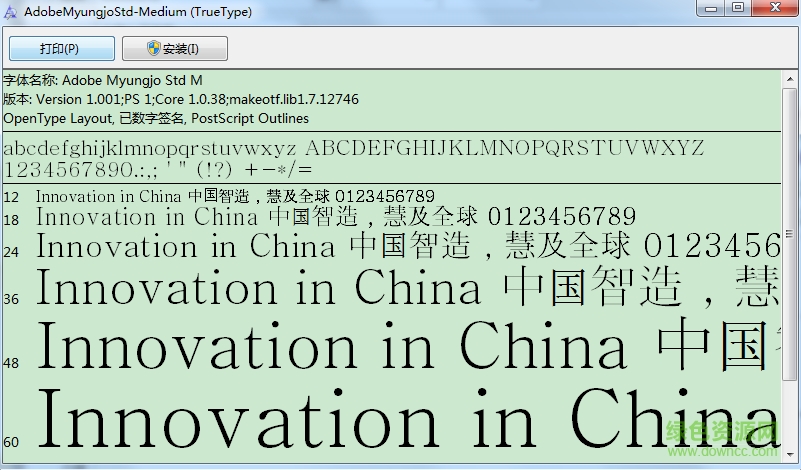
adobe myungjo std m中是一款很有特色的英文字體,這款字體結(jié)構(gòu)端正,字跡清晰,比較適合用于藝術設計、廣告設計等方面,需要這款字體的朋友歡迎來綠色資源網(wǎng)免費下載使用。
adobe myungjo std m字體是一款很不錯的電腦英文字體,寫出來的字很美觀、大方,喜歡的朋友就快來綠色資源網(wǎng)下載吧。